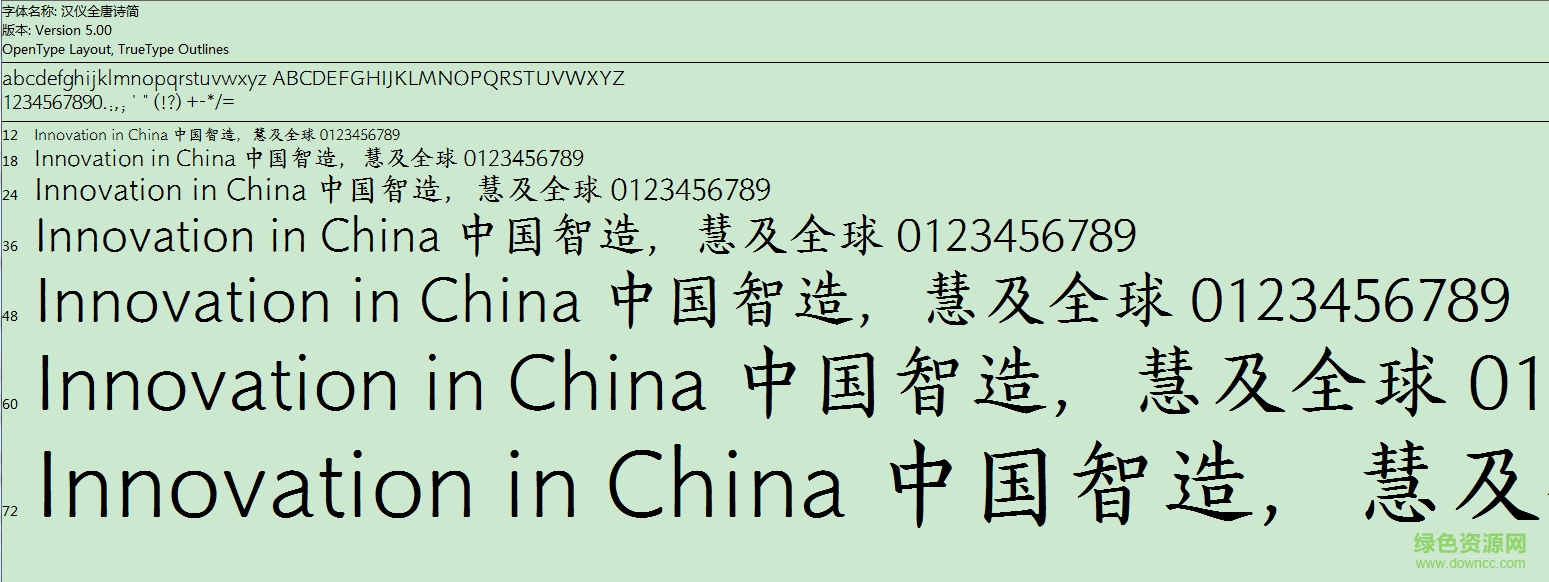
hyquantangshij字體是一款漂亮好看的漢儀字體,該字體線條清晰,筆畫流暢,整體效果十分出色,喜歡的朋友快來綠色資源網(wǎng)下載收藏吧!
hyquantangshij是一款應(yīng)用于正文的簡(jiǎn)體中文字體,字形略微偏長(zhǎng),中宮收緊,秀美圓潤(rùn),帶寫刻風(fēng)格,體現(xiàn)高雅氣質(zhì)感,可廣泛應(yīng)用于正文標(biāo)題、廣告設(shè)計(jì)、平面設(shè)計(jì)、印刷包裝等領(lǐng)域!